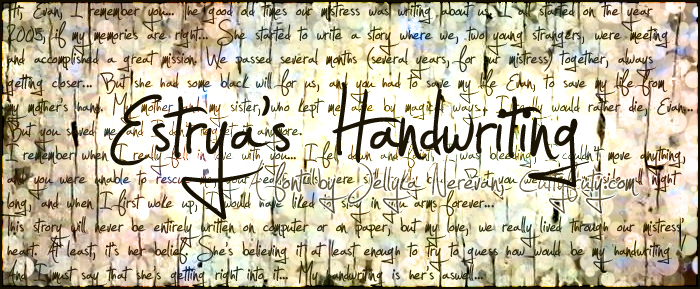
Jellyka - Estrya's Handwriting
"Jellyka - Estrya's Handwriting" è un font scritto a mano gratuito, creato da CuttyFruty.com nel 2008 e caratterizzato da tratti ariosi e un ritmo personale. Lunghe linee sinuose circondano le lettere, mentre il tratto fine e veloce rende la scrittura aggraziata anziché formale.
I suoi riccioli generosi creano un senso di movimento perfetto per partecipazioni di nozze e branding nel settore beauty, dando a nomi e frasi brevi l'aspetto di una firma sicura. Questo font gratuito può anche aggiungere un tocco intimo e raffinato al packaging di boutique, testate editoriali, grafiche per i social media e cancelleria personale, specialmente se abbinato a una tipografia sobria e molto spazio bianco.
Aggiornamento 2010: ho modificato le metriche affinché non risulti troppo piccola.